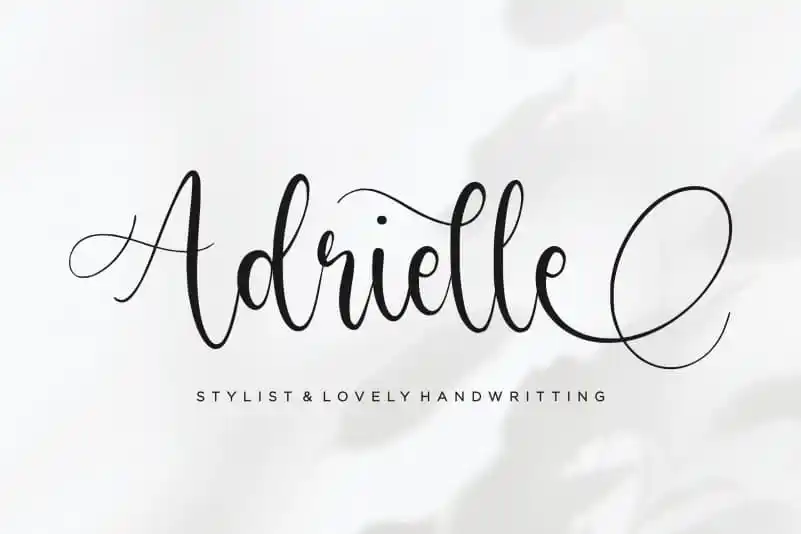
Adrielle Handwritting Font – Download Grátis
A Adrielle Handwriting Font é uma exquisite coruja para designers apaixonados por letras serifadas com sutis detalhes que criam um ar elegante e delicado. Suas linhas fluidas e harmoniosas são ideais para aplicar em criações de pacotes de produtos, projeto de marca, revistas, redes sociais, casamentos ou simplesmente para expressar palavras acima de fundos mais complexos. Esta fonte é perfeita para dar um toque especial a qualquer design gráfico, seja com sua utilização em estilos vintage e sofisticados ou no entrelaçamento suave dos caracteres que se tornam ainda mais impactantes quando vistas em grandes tamanhos. O seu designer, balpirick, tem criado uma opção única que permite aos designers expressar sua arte de maneiras inovadoras e memoráveis.